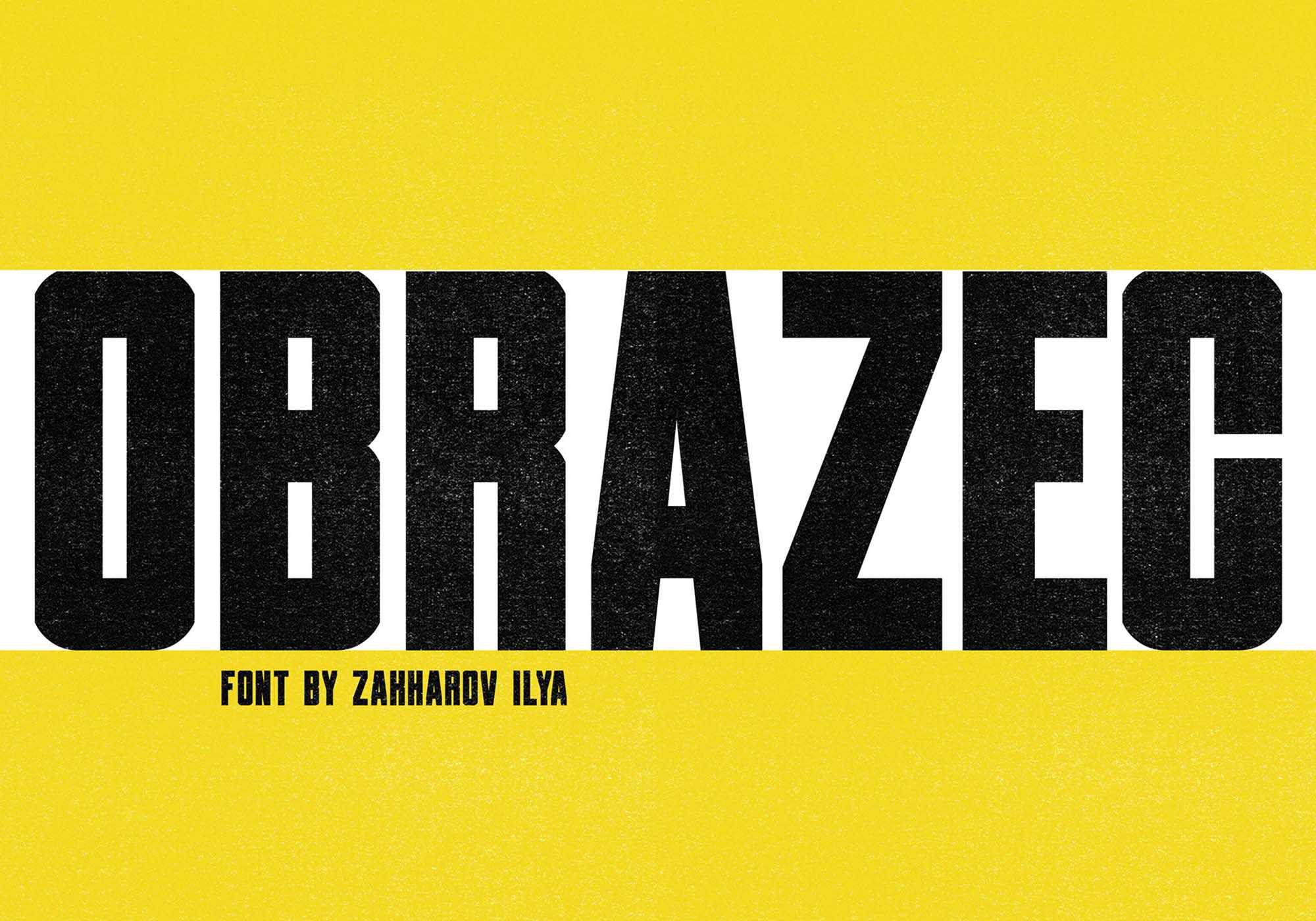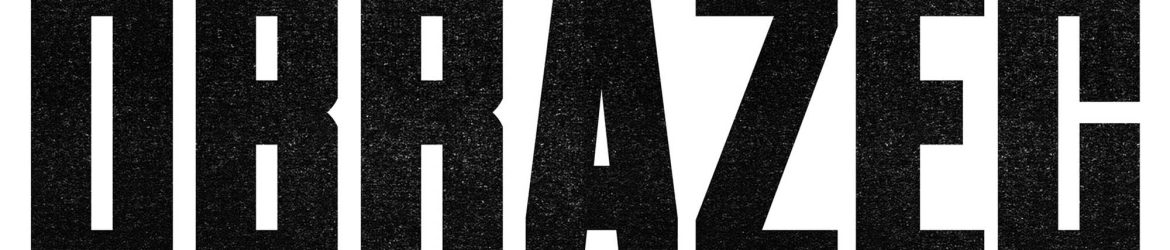
A Obrazek Sans Serif Font é uma solução cuidadosamente projetada para a categoria de mockups, destinada a fornecer todos os recursos necessários para criar e perfeitamente desenhar um logotipo ou marca. Como indivíduos que deixamos uma impressão duradoura, empresários também desejam que seu negócio tenha uma primeira impressão positiva. Para atender a essa necessidade, compartilhamos Obrazek. Obrazek é uma fonte sans serif industrial, projetada pelo Ilya Zakharov. Esta fonte industrial representa uma opção segura e moderna para projetos que buscam uma aparência sóbria e clara. Com Obrazek, você tem a oportunidade de traduzir sua ideia de marca em uma arte perfeita, garantindo que a imagem que você tem em mente corresponda ao resultado final. Ideal para designers e criativos que buscam uma fonte de qualidade para seus projetos de logotipo ou marca.